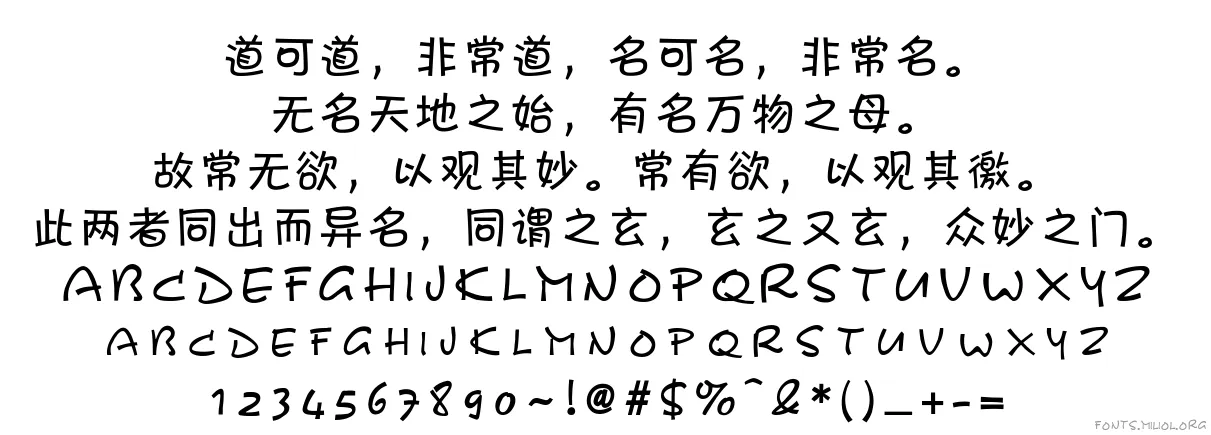
## 方正卡通简体:一款充满童趣的中文字体
方正卡通简体(FZKaTong-M19S)是由北大方正电子有限公司设计开发的一款极具特色的中文字体。这款字体以其圆润的笔画、活泼的造型和鲜明的卡通风格而著称,特别适合用于儿童读物、卡通漫画、广告设计等需要营造轻松愉快氛围的场合。
该字体采用GB2312-80标准编码(FZKATJW--GB1-0),包含6763个常用汉字和符号,能够满足日常设计需求。其笔画设计保留了手写体的自然流畅感,每个字符都呈现出憨态可掬的视觉效果,既保持了汉字的基本结构,又通过夸张的转角处理和饱满的字形赋予了文字独特的生命力。
在实际应用中,方正卡通简体能够有效提升设计作品的亲和力和趣味性。无论是幼儿园的识字卡片、儿童绘本的标题,还是游乐园的宣传海报,这款字体都能为作品增添一抹亮丽的色彩。其清晰易读的特性也确保了信息传递的有效性,是设计师创作卡通风格作品时的理想选择。